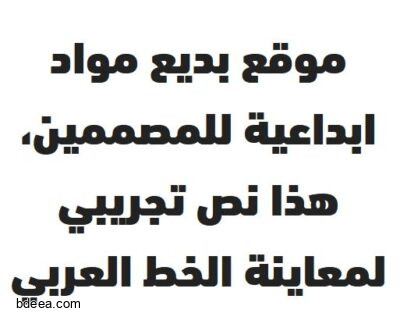
تحميل خط عربي Greta Arabic Bold Italic
تحميل خط عربيfont download Greta Arabic Bold Italic يضيف لمسة فنية رائعة الى التصاميم العربية والمطبوعات والعروض التقديمية بالكلمات العربية والارقام بشكل مميز يمكنك تثبيته على جهازك والبدء باستخدامه في برامج التصميم
يتميز بالخط بالمرونة والخفة والشكل الانيق في الكتابة والحروف يمكن معاينته وتجربة استخدامه ليضيف لك تميز الى تصاميمك